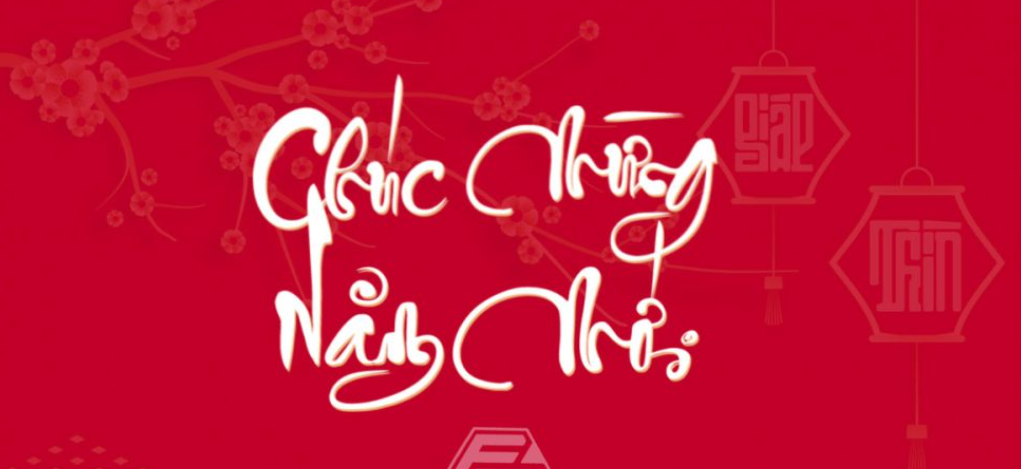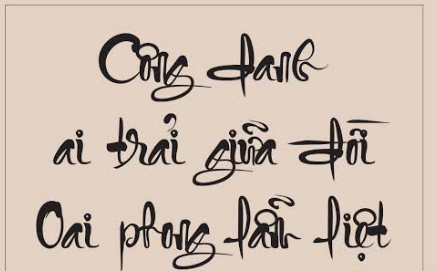
Font Fz Tiểu Tự Việt hóa là bộ phông chữ thư pháp thuần Việt được sáng tạo bởi FzTeam, nổi bật với phong cách viết bút lông nét nhỏ, gọn gàng, thanh tao và cực kỳ trang trọng. Khác với các dòng thư pháp đại tự (chữ lớn) có nét bút phóng khoáng, Fz Thư pháp Tiểu Tự được thiết kế tối ưu cho các đoạn văn bản dài, câu đối chúc xuân, thơ ca hoặc các thông tin chi tiết trên bao bì lễ hội. Doozypack.vn cung cấp link tải trọn bộ phông chữ chuẩn kỹ thuật, giúp bạn sở hữu Bộ Font Fz Việt hóa chất lượng cao, hỗ trợ tiếng Việt hoàn chỉnh để tự tin thiết kế bao bì và bộ nhận diện thương hiệu truyền thống.
Đặc điểm thẩm mỹ độc đáo của bộ font Fz Thư pháp Tiểu Tự
Fz Tiểu Tự tái hiện trọn vẹn vẻ đẹp của nghệ thuật thư pháp chữ Quốc ngữ, nơi sự nắn nót, tỉ mỉ và nét bút thanh mảnh được đặt lên hàng đầu.
Phong cách thư pháp Việt Nam nét nhỏ tinh tế và gọn gàng
Đặc trưng lớn nhất của Font Fz Tiểu Tự Việt hóa là cấu trúc nét chữ mảnh mai, các đường đưa bút lên xuống nhịp nhàng nhưng không bị lan rộng quá khổ. “Tiểu tự” (chữ nhỏ) giúp phông chữ này giữ được sự ngăn nắp, thanh lịch, rất phù hợp để trình bày các nội dung có nhiều chữ như lời chúc Tết trên bao lì xì, bài thơ trên hộp bánh Trung thu hoặc câu đối trên hộp quà doanh nhân.
Cấu trúc chữ tối ưu cho các câu đối và thơ ca truyền thống
Các ký tự trong Bộ Font Fz Việt hóa sở hữu tỷ lệ chiều cao đồng đều, trục chữ thẳng đứng chuẩn mực giúp các dòng thơ lục bát hoặc song thất lục bát khi dàn trang luôn giữ được sự ngay ngắn, trang nghiêm nhưng vẫn đượm đà hồn thơ dân tộc.
Ưu điểm nổi bật của Bộ Font Fz Việt hóa
Được thiết kế nguyên bản bởi các nhà sáng tạo Việt Nam, hệ thống font Fz giải quyết hoàn hảo mọi vấn đề về ngôn ngữ mà các designer thường gặp phải:
- Chuẩn xác tuyệt đối về bộ dấu tiếng Việt: Vì là phông chữ “Made in Vietnam”, Fz Tiểu Tự sở hữu hệ thống dấu sắc, huyền, hỏi, ngã, nặng được đặt ở vị trí hoàn hảo, ôm khít lấy thân chữ, không gây cảm giác chắp vá hay làm đè nét.
- Đa dạng ứng dụng truyền thống: Trọn bộ font Fz mang lại hệ sinh thái phong phú để bạn kết hợp giữa các tiêu đề lớn và phần nội dung chữ nhỏ truyền thống.
Lời khuyên từ xưởng in: Vì Fz Tiểu Tự có các nét chữ thư pháp khá thanh mảnh, khi bạn thiết kế in ấn trên chất liệu giấy có bề mặt nhám thô như giấy Kraft, hãy để kích thước chữ tối thiểu từ 10pt trở lên và ưu tiên sử dụng định dạng OTF để nét chữ không bị mất chi tiết.
Ứng dụng thực tế của font Fz Tiểu Tự trong sản xuất bao bì tại Doozypack.vn
Sự thanh tao và mang đậm dấu ấn văn hóa của Fz Tiểu Tự mang lại hiệu ứng thị giác đắt giá trên các dòng sản phẩm bao bì thực tế do Doozypack.vn sản xuất:
- Hộp bánh Trung thu & Hộp quà Tết: In các câu chúc năm mới hoặc bài thơ truyền thống bằng font Fz Tiểu Tự trên nắp hộp giấy giúp sản phẩm toát lên vẻ đẹp trang trọng, hoài cổ và vô cùng tinh tế.
- Bao lì xì nghệ thuật: Nét chữ nhỏ gọn, nắn nót rất phù hợp để in các câu đối ngắn trên mặt sau của bao lì xì, tạo nên món quà tinh thần ý nghĩa cho người nhận.
- Hộp trà thảo mộc & Nông sản mộc mạc: Dùng cho phần câu chuyện thương hiệu hoặc mô tả sản phẩm, giúp bao bì toát lên phong cách mộc mạc, gần gũi và đậm đà bản sắc Việt.
Lưu ý kỹ thuật khi in ấn với phông chữ thư pháp nét nhỏ Fz
Việc sản xuất bao bì thực tế sử dụng các phông chữ thư pháp nét thanh mảnh đòi hỏi sự am hiểu kỹ thuật chuyên sâu tại xưởng in Doozypack.vn:
- Kiểm soát độ dày nét Hairline khi gia công: Các nét đưa bút của Fz Tiểu Tự khá mảnh. Khi gia công ép kim vàng (Hot Stamping) hoặc dập nổi, designer nên đảm bảo nét chữ có độ dày tối thiểu 0.15mm để nhũ bám dính sắc nét, không bị đứt đoạn.
- Chọn chất liệu giấy phẳng mịn: Fz Tiểu Tự đẹp nhất khi in trên giấy Ivory, Couche hoặc giấy mỹ thuật nhẵn. Tránh in các nét chữ quá thanh trên bề mặt giấy Kraft thô nhám vì mực dễ bị loang làm mất đi độ sắc sảo của nét chữ.
Doozypack.vn không chỉ cung cấp kho tài nguyên thiết kế miễn phí mà còn trực tiếp sản xuất hộp giấy, túi giấy và tem nhãn theo yêu cầu. Với nét chữ mang đậm tinh thần Á Đông và vẻ đẹp giàu tính nghệ thuật của Font FZ Tiểu Tự, đội ngũ kỹ thuật sẽ hỗ trợ kiểm tra file, cân chỉnh bố cục và tư vấn cách thể hiện phù hợp để từng đường nét khi in lên giấy vẫn rõ ràng, sắc sảo, hạn chế nhòe mực và góp phần truyền tải dấu ấn riêng của thương hiệu. Nếu muốn ứng dụng font vào thiết kế bao bì, bạn có thể tham khảo dịch vụ in hộp giấy theo yêu cầu của Doozypack.vn.